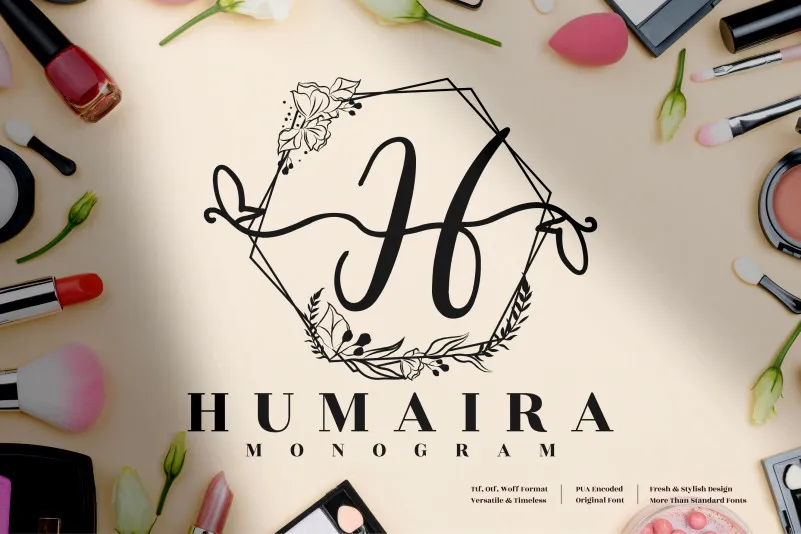
A Humaira Monogram Font é uma elegante tipografia decorativa que traz ornamentos de folha de luxo para seus projetos digitais e impressos. Seu estilo autêntico se destaca ao criar cartões de agradecimento charmosos, arte de material para estacionamento arrebatadoras e postagens nas redes sociais atrativas, além de logotipos memoráveis. Esta fonte é perfeita para designers que buscam dar um toque especial aos seus projetos de apresentação pessoal e marketing. Seja você uma designer de moda criando rótulos de produtos personalizados ou um fotógrafo estiloso buscando articular seu trabalho através de cartões postais únicos, a Humaira Monogram Font é uma escolha perfeita para agregar elegância e sofisticação a suas criações.